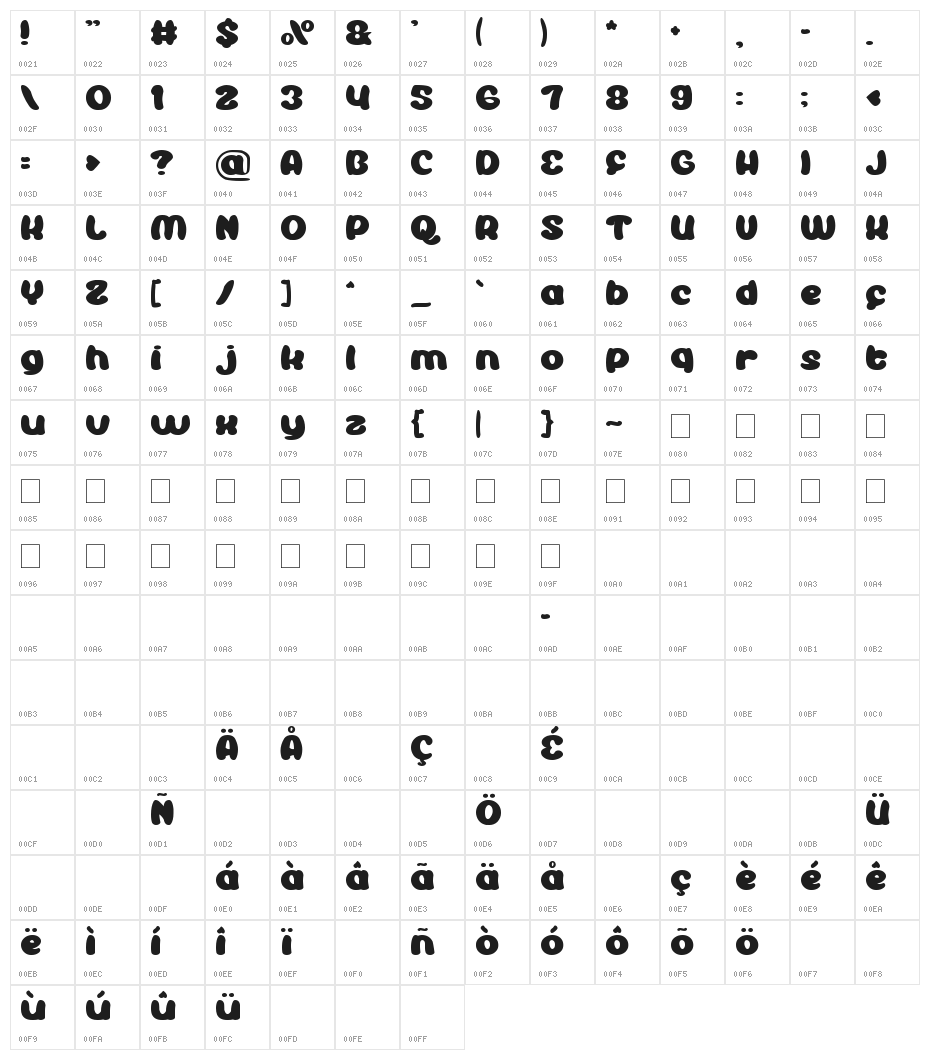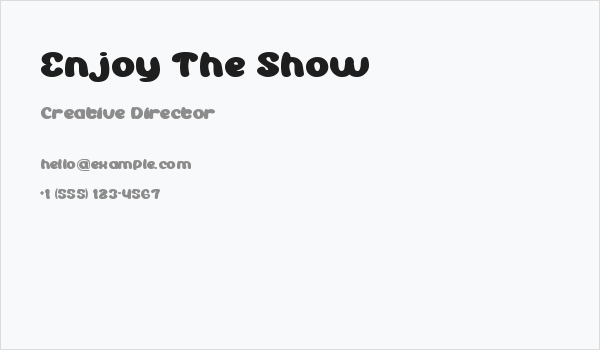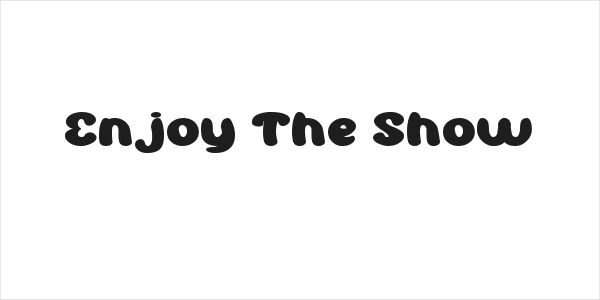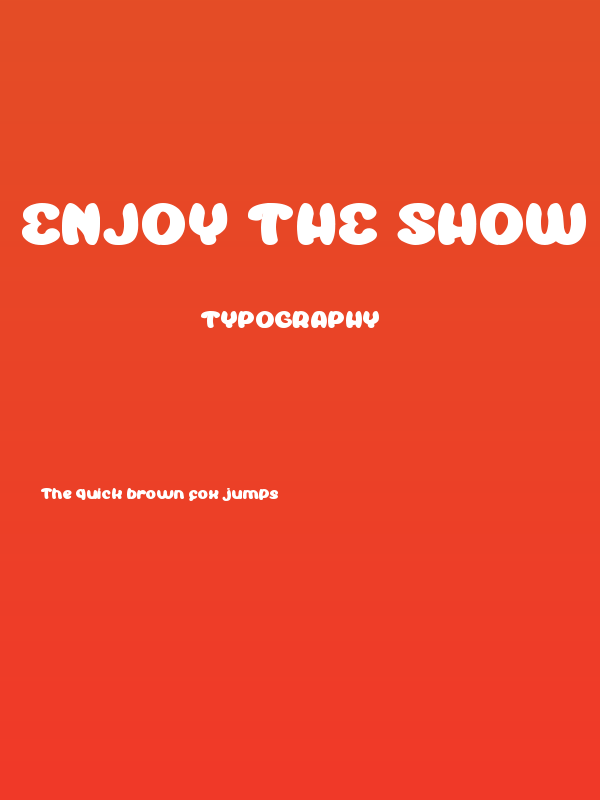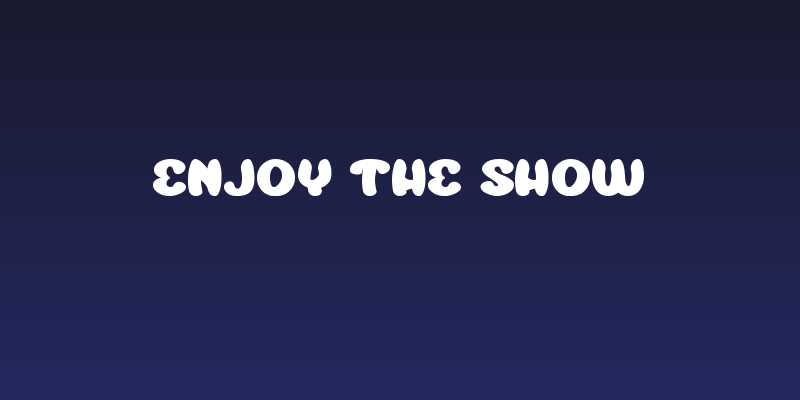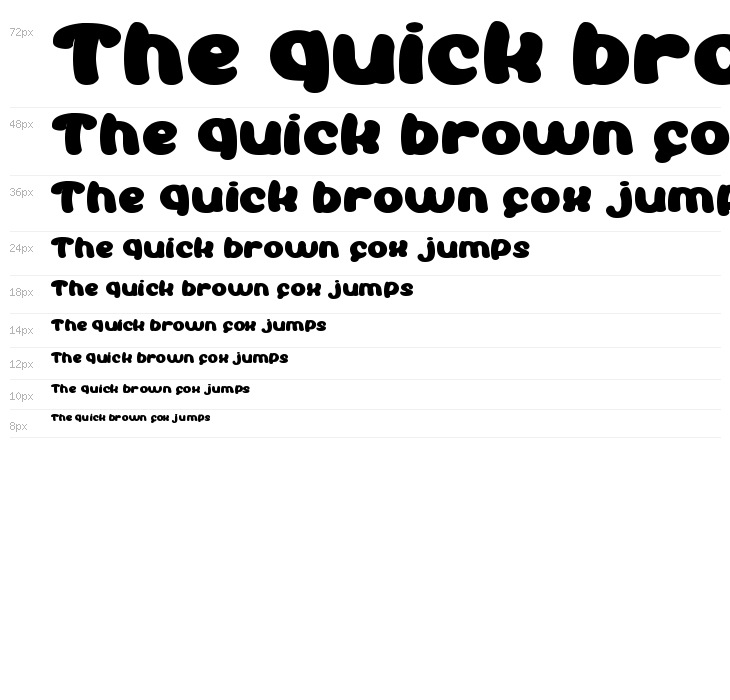
Enjoy The Show Font
| Stile generale | Playful, Fun |
| Progetti proposti | Ideal for children's books, party invitations, playful branding, and eye-catching posters. |